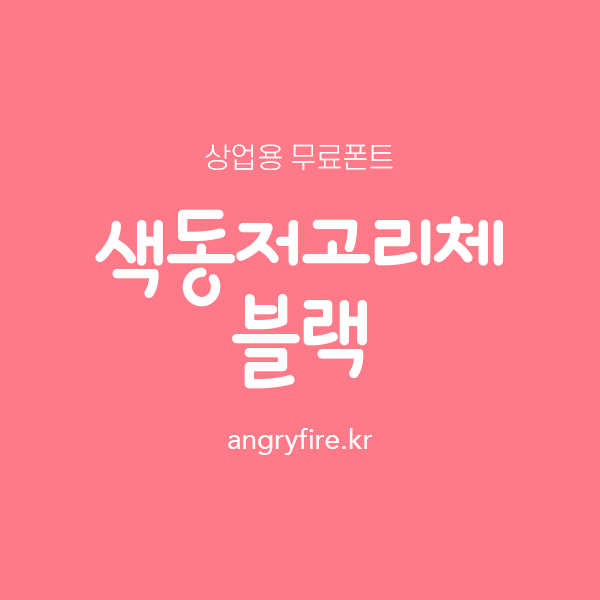
진짜 리얼 손글씨 솔폰트의
'색동저고리체 블랙'을 소개합니다.
캘리그라피 전문폰트 솔폰트의 설치형폰트(TTF)는 글꼴의 특성에 따라 붓의 질감(윤곽선)이 살아있는 디테일(Detail)타입과 윤곽선을 단순화 시킨 매끈타입(Smooth) 2종으로 구성되어 있습니다. 조합형폰트는 자음과 모음을 적절히 조합 배열하여 더욱 다양하고 특별한 폰트를 구성하실 수 있으며, 제목, 로고, 브랜드 등 개성있는 서체로 활용하기에 적합합니다.